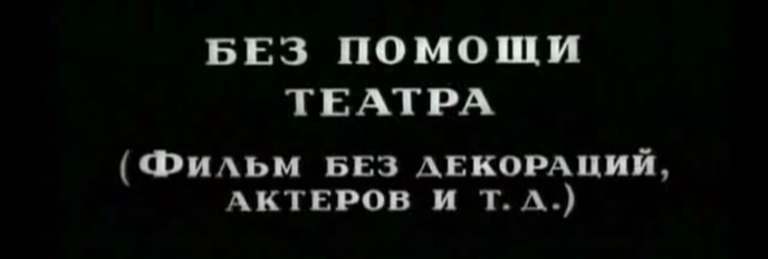
schrift aus "man with a movie camera" (1929)
suche verzweifelt nach dieser kyrillischen schrift:
mit dieser möchte ich einen englischen text schreiben.
hab schon whatthefont und identifont durch... ohne erfolg.
besonders das "M" und "N" kann ich in dieser art nicht finden.
das "N" im bild hätte ich als ein gespiegeltes lateinisches gesehen.
ganz recht, ich bin aus suche nach der lateinischen version dieser schriftart, oder zumindest etwas ähnlichem.
das "N" im bild hätte ich als ein gespiegeltes lateinisches gesehen. …
Das kyrillische "и" entspricht dem lateinischen "i".
das kyrillische "i" im bild hätte ich als ein gespiegeltes lateinisches "N" gesehen.
Ich vermute, dass lampeanaus einfach nach einer Schrift für’s Lateinische mit hohem Strichstärkenkontrast und »slab-artigen Serifen« sucht. Die Experten kennen das sicher einiges.
Das Bild ist allerdings ein schönes Beispiel für kyrillische Kapitälchen (»БЕС АКТЕРОВ« statt »бес актеров«). Danke! :-P